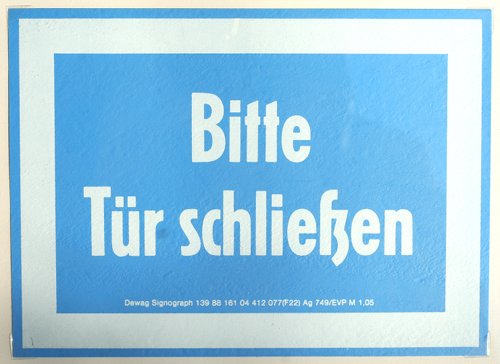
Wer kann mir ein einzelnes ß in ſʒ-Form »mit Schwänzchen oben« setzen?
Als Aufhänger für eine deutsche Konversationsrunde möchte ich ein paar Eszetts zeigen, sowohl kleine als auch große, in Antiqua und Fraktur. Ich habe Schriften mit fast allen Formen. Nur eine Antiqua/Grotesk mit der ſʒ-Form »mit Schwänzchen oben«, also so wie auf den Berliner Straßenschildern oder der neuen BER-Hausschrift, fehlt mir.
Mag mir jemand solch ein einzelnes ß setzen? (Alternativ: Kann jemand eine kostenlose Schrift mit solch einem ß empfehlen?)
Falls sich jemand für das Ergebnis meiner Minidemo (PDF 87K) zum Eszett (und am Ende ein ganz bisschen ſ) interessiert … (für mich interessanteste Reaktionen [highlight]gehighlighted[/highlight])
Ich habe zuerst 4 Mal allein stehende (Minuskel-)Eszetts gezeigt, jeweils in einer Serifen- und serifenlosen Schrift in Sulzbacher und ſs-Form. Alle im Publikum (amerikanische Deutschlehrer, Deutschschüler ab 16, deutsche Emigranten) haben auf Anhieb erkannt, dass alle vier Bilder ein ß zeigten. Obwohl ich explizit danach gefragt habe, [highlight]konnte niemand einen Unterschied zwischen Sulzbacher und ſs-Form erkennen[/highlight].
Bei der ſʒ-Form wurde es schon schwieriger: die Lehrer und Emigranten wollten anscheinend nichts falsches sagen und haben sich deshalb nicht getraut, das gezeigte Bild als ß zu identifizieren. Ein Schüler hat (mit wenig Zuversicht) richtig geraten, vielleicht weil eben vorher schon 4 Eszetts gezeigt worden waren. Im Kontext konnten dann aber alle auch dieses ß problemlos lesen.
Danach kam ein allein stehendes β. Ein Schüler riet auch hier (diesmal mit mehr Zuversicht) Eszett; aber die Lehrer und Emigranten haben sofort unisono protestiert: nein, das sei ein Beta!
Dann kamen zwei [highlight]allein stehende ẞ[/highlight] dran. Damit [highlight]konnte auf Anhieb niemand etwas anfangen[/highlight]. (Von den Anwesenden war niemand in den letzten 3 Jahren in Deutschland gewesen.) [highlight]Im Kontext war aber allen sofort klar, dass es sich um Eszetts handelte[/highlight].
Ganz zum Schluss habe ich meine Testzeile (»Tür schließen«) noch 2 Mal in Fraktur gezeigt (natürlich mit 7B.png). Weder ß noch ſ bereiteten Probleme. Ich habe auch extra nach dem ſ gefragt: die Emigranten (allesamt überdurchschnittlich gebildet) kannten es aus dem (groß)elterlichen Bücherschrank, die Amerikaner aus dem Geschichtsunterricht.
Der Aufhänger der ganzen Sache war dieses Schild, das über meiner Haustür hängt:
Obwohl ich explizit danach gefragt habe, [highlight]konnte niemand einen Unterschied zwischen Sulzbacher und ſs-Form erkennen[/highlight].
Das überrascht mich nicht und es dürfte hierzulande außerhalb von Designerkreisen nicht anders sein. Was dann auch das Politikum um die vermeintlich falsche und richtige Form der beiden ad absurdum führt.
Na gut, aber ziehen du und die meisten deiner Schrift gestaltenden Kollegen das ſs-ß nicht mittlerweile klar vor? Ist also nicht diese Form in euren Augen das richtigere?
Und warum bevorzugt ihr die Form so klar? Geht es euch nur um eine bessere Abgrenzung zum B und/oder β?